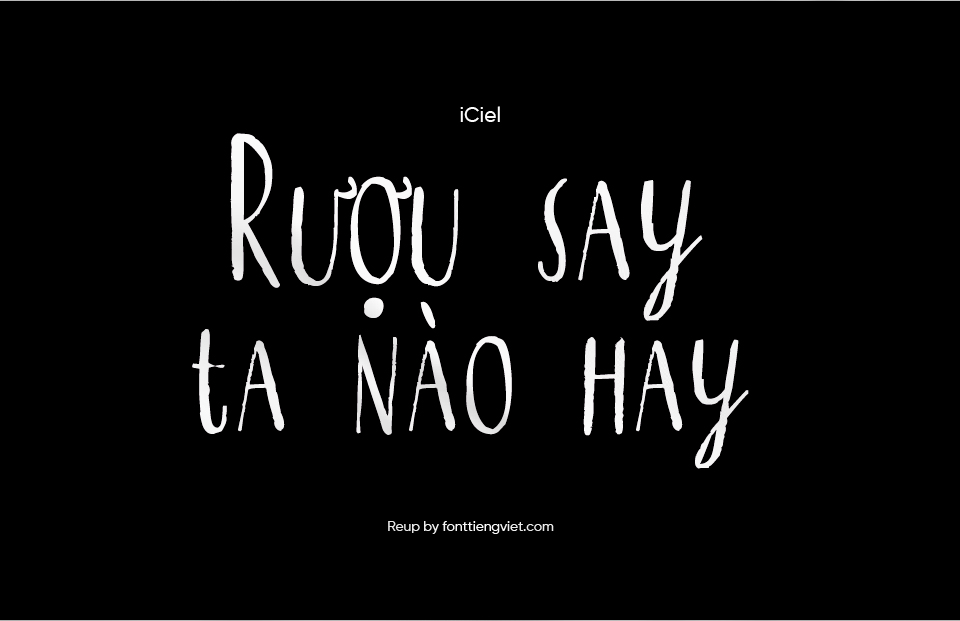
Tải Ngay Font việt hóa iCiel Qiber – Font Chữ Brush Độc Đáo Cho Thiết Kế
Giới thiệu về Font việt hóa iCiel Qiber
Trong thế giới đồ họa hiện đại, việc tìm kiếm một bộ Font Chữ mang phong cách viết tay phóng khoáng là điều vô cùng quan trọng. Font việt hóa iCiel Qiber chính là sự lựa chọn hoàn hảo dành cho những ai yêu thích vẻ đẹp tự nhiên và cá tính. Đây là một bộ font thuộc phong cách Brush Script với các đường nét mạnh mẽ, uốn lượn nhưng vẫn đảm bảo sự mềm mại cần thiết cho các tác phẩm nghệ thuật.
Đặc điểm nổi bật của iCiel Qiber
Bộ font này được iCiel tinh chỉnh kỹ lưỡng, hỗ trợ đầy đủ bảng mã tiếng Việt giúp các bạn học sinh và nhà thiết kế dễ dàng sử dụng trong mọi phần mềm đồ họa. Với những nét cọ được mô phỏng chân thực, iCiel Qiber mang lại cảm giác thủ công đầy cảm hứng, giúp bài thuyết trình hay các ấn phẩm trường học trở nên sinh động và gần gũi hơn bao giờ hết.
Ứng dụng thực tế của Font việt hóa iCiel Qiber
Nhờ tính ứng dụng cao, iCiel Qiber thường xuyên xuất hiện trên các bìa sách, poster sự kiện hay các mẫu thiệp chúc mừng. Trong môi trường giáo dục, giáo viên và học sinh có thể dùng font này để trang trí báo tường hoặc thiết kế slide bài giảng nhằm thu hút sự chú ý. Sự kết hợp giữa phong cách cổ điển và hiện đại giúp bộ font không bao giờ lỗi mốt.
Lưu ý khi sử dụng trong thiết kế
Mặc dù iCiel Qiber rất đẹp nhưng bạn nên sử dụng cho các tiêu đề lớn thay vì các đoạn văn dài để tránh gây rối mắt. Việc kết hợp font này với các kiểu chữ không chân đơn giản sẽ tạo nên sự cân bằng tuyệt vời cho bố cục tổng thể.